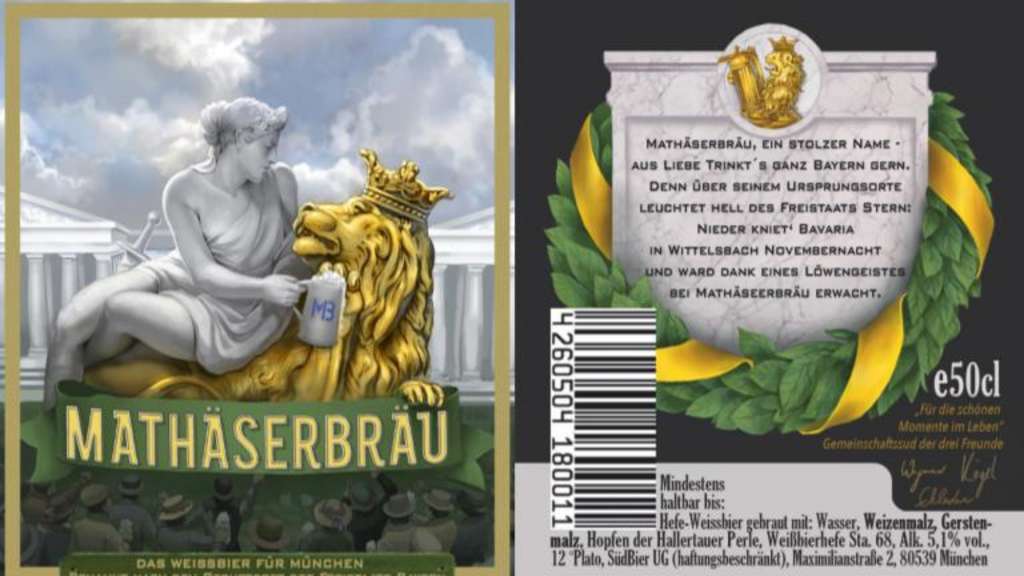
Alte (?) Schrift gesucht - aufwändig - gestrichelter Schatten
die beigefügte Schriftart einer alten Brauerei hat es mir angetan. Ich vermute allerdings, dass es sich dabei um eine von Hand gemalte Schrift handelt - oder liege ich falsch und die Lösung ist ganz einfach?